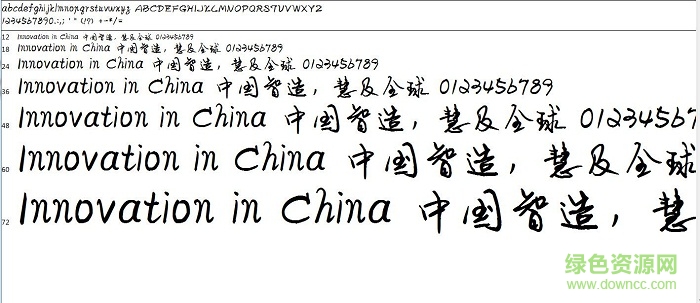
漢儀隨風(fēng)瀟灑體ttf是一款線條灑脫奔放的漢儀字體,結(jié)構(gòu)簡省,筆形富于變化,靈動優(yōu)雅,極富意趣,可以用于海報設(shè)計、古風(fēng)設(shè)計或是裝飾用字,喜歡的朋友快來下載吧!
該字體線條飄逸任性,筆風(fēng)隨意大膽,字形飄逸,極具創(chuàng)意,整體效果非常的出色!